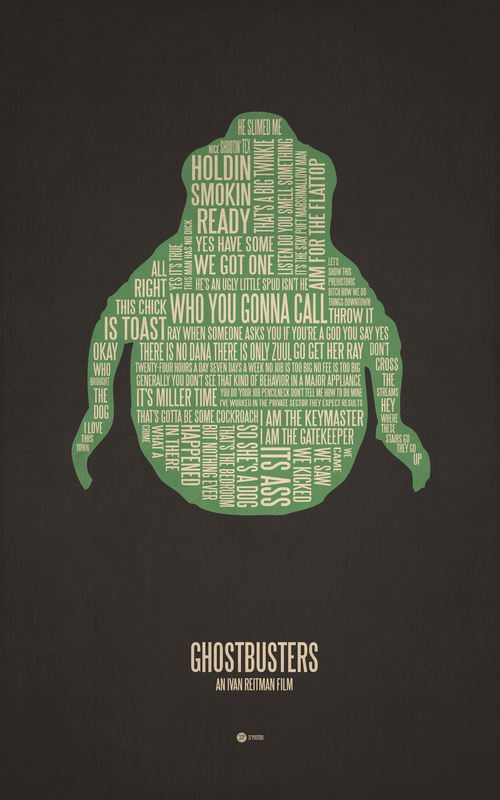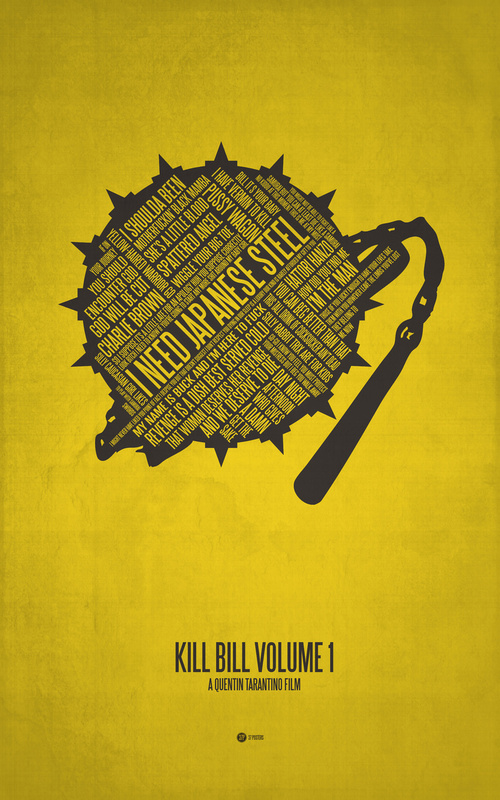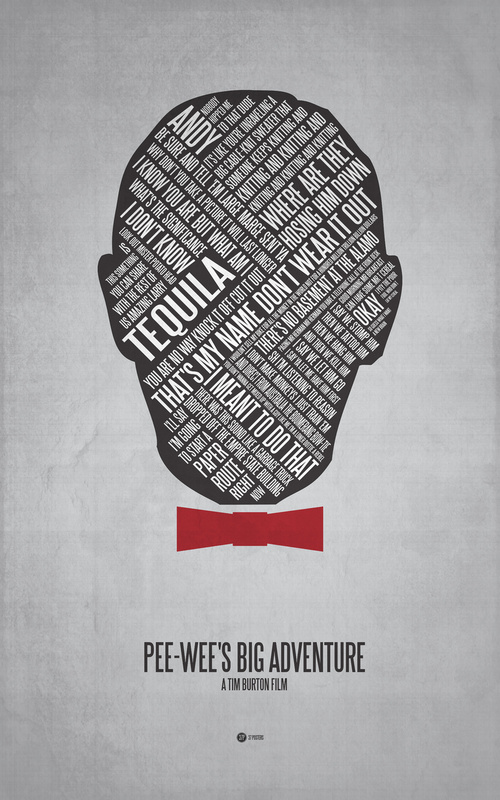
Posters de films en typographie
Regardez les superbes posters typographique de Jerod Gibson. Ce sont des reprises de films connus comme StarWars, Ghostbusters ou encore KillBill. Minimalistes et typographiques, ils sont en plus à vendre à moins de 20$.